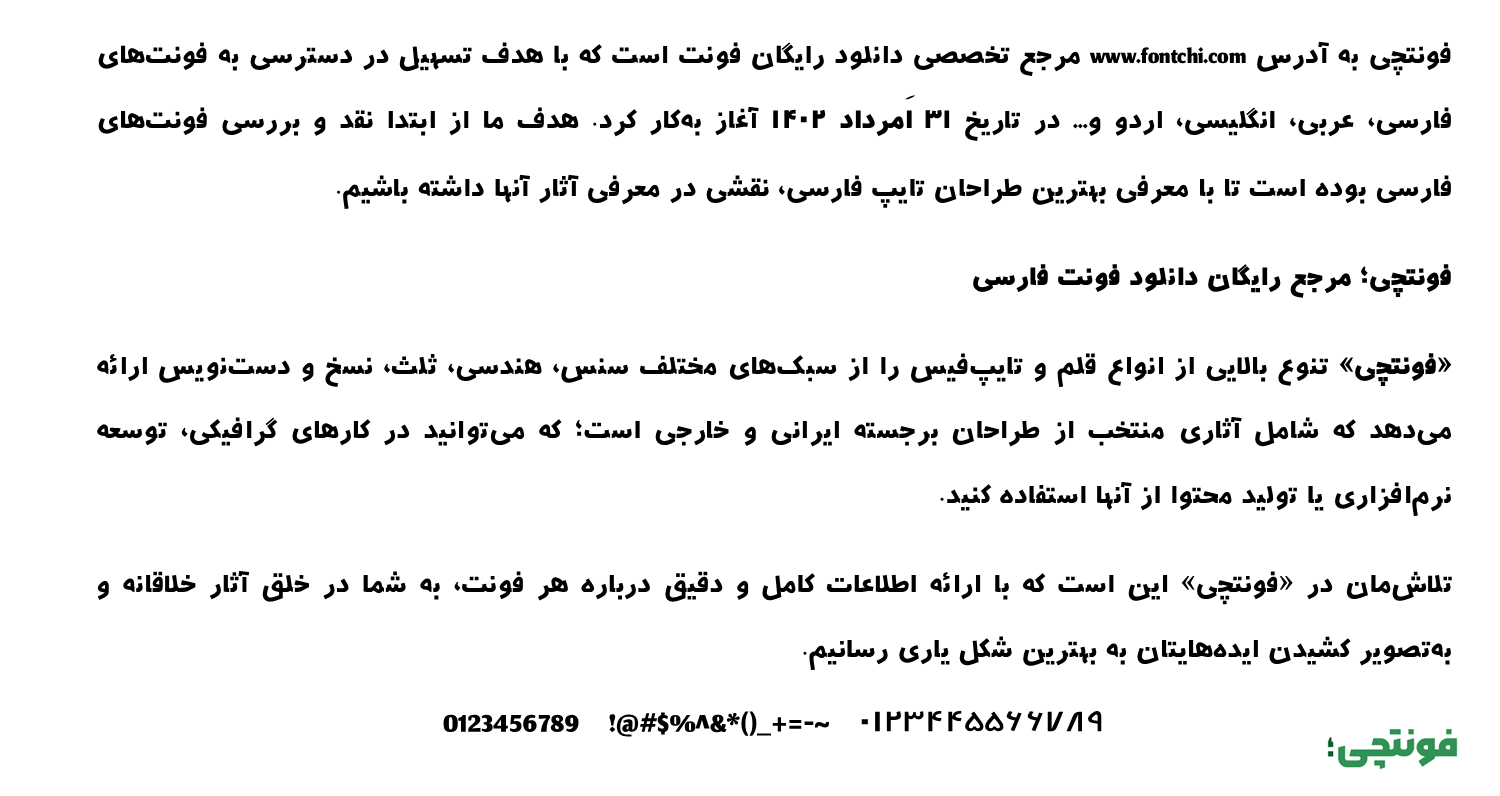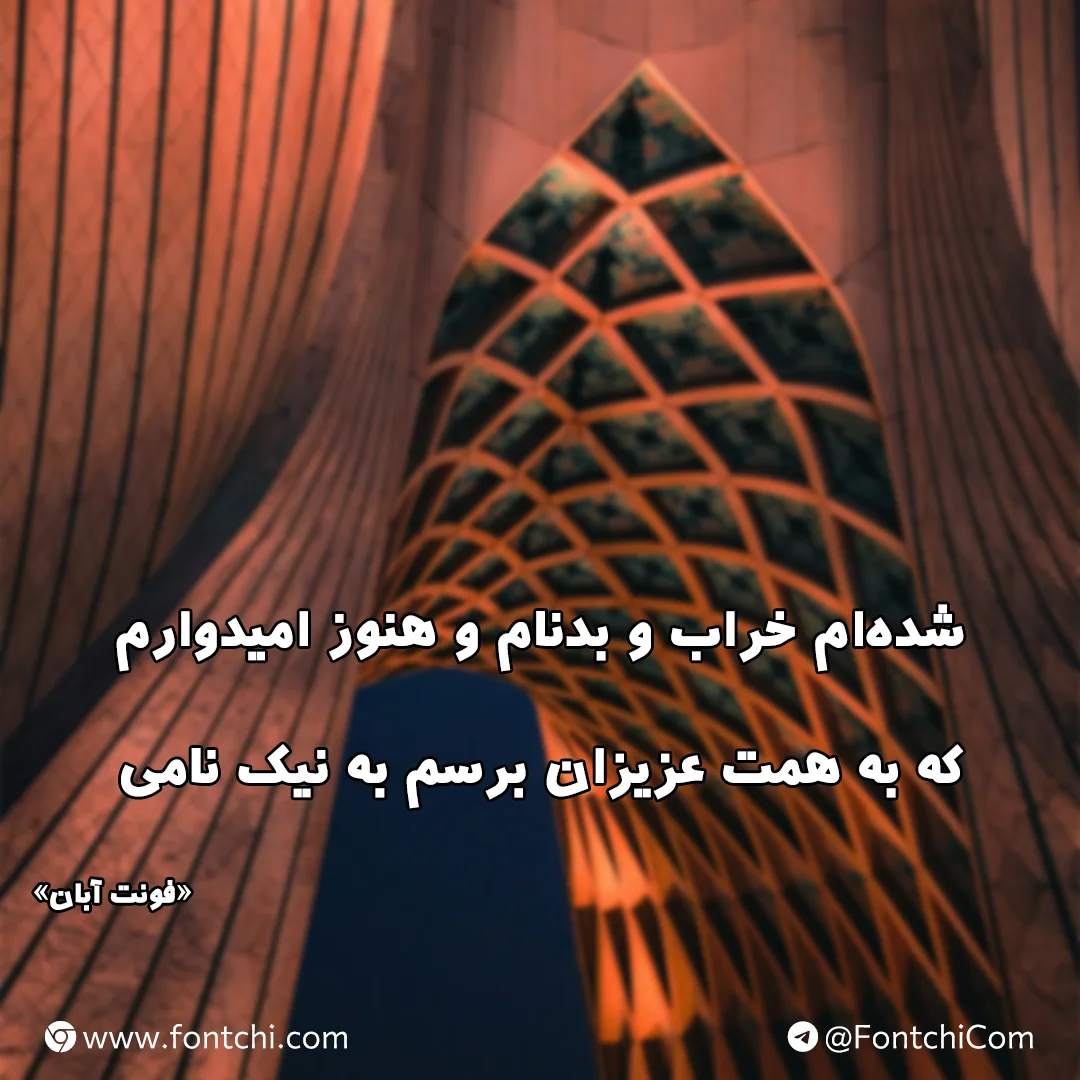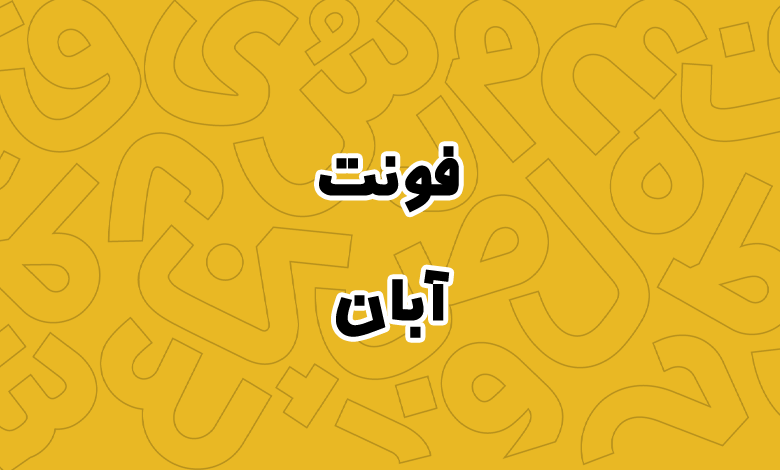
فونت آبان (Aban)
فونت آبان (به انگلیسی: Aban) از سری فونتهای فانتزی به سبک سنس است که دارای ظاهری دوستانه و مناسب برای متون کوتاه تا بلند است. این فونت از سه وزن پشتیبانی میکند که میتوانید در موضوعاتی مثل مطبوعات، عکس نوشتهها و کتب یا مجلات از آن استفاده کنید.
فونت آبان توسط مریم کهوند طراحی شده است و دارای ظاهری نزدیک به فونت یکان است با این تفاوت که بهای زوایا و منحنیهای گرد دارای شکستگیهای اجباری است که ظاهر کلی فونت را نیز تا حدودی کمی ایتالیک کرده است. در ادامه بیشتر با این فونت آشنا میشویم.
دانلود فونت آبان (Aban) مناسب متون
فونت فارسی آبان محدود به این زبان نیست. این فونت رایگان برخلاف دیگر فونتها از نهتنها از زبان عربی و انگلیسی پشتیبانی میکند، بلکه بسیاری از گلیف زبانهای لاتین همچون فرانسه، ایتالیا، اسپانیا و ترکی استانبولی را نیز در خود دارد که میتوانید از آن در پروژههای چندزبانه استفاده کنید.
این فونت در بخش اعداد دارای اعداد فارسی است و استاندارد اعداد فارسی «۰۴۵۶» را رعایت کرده است. اما برای اعداد عربی نیز از همین نسخه اعداد فارسی استفاده شده که شاید تنها کاستی فونت باشد. در بخش اعراب و کاراکترهای خاص نیز در هر زبان به خوبی این گلیفها در همنشینی یکدیگر قرار دارند.
با دانلود فونت آبان به ۳ نسخه وزنی دسترسی دارید. نسخه نازک (Light) که میتوانید برای متونی که اهمیت کمتری در متن دارد استفاده کنید؛ نسخه معمولی (Regular) که میتوانید برای بدنه اصلی متن استفاده کنید و نسخه ضخیم (Bold) که میتوانید برای تیترها از آن بهره ببرید.
این فونت برای استفاده در متون بلند تا کوتاه کاربردی است. از وزنهای نازک و معمولی میتوانید در متون کوتاه و از وزن بولد در متون کوتاه و تیترها استفاده کنید. برخی کاربردهای این قلم عبارتند از:
- متن بدنه اصلی و جلد کتاب و مجلات
- طراحی پوستر و بنر در صنعت چاپ و مطبوعات
- استفاده در تامنیل ویدئوها و پست شبکههای اجتماعی